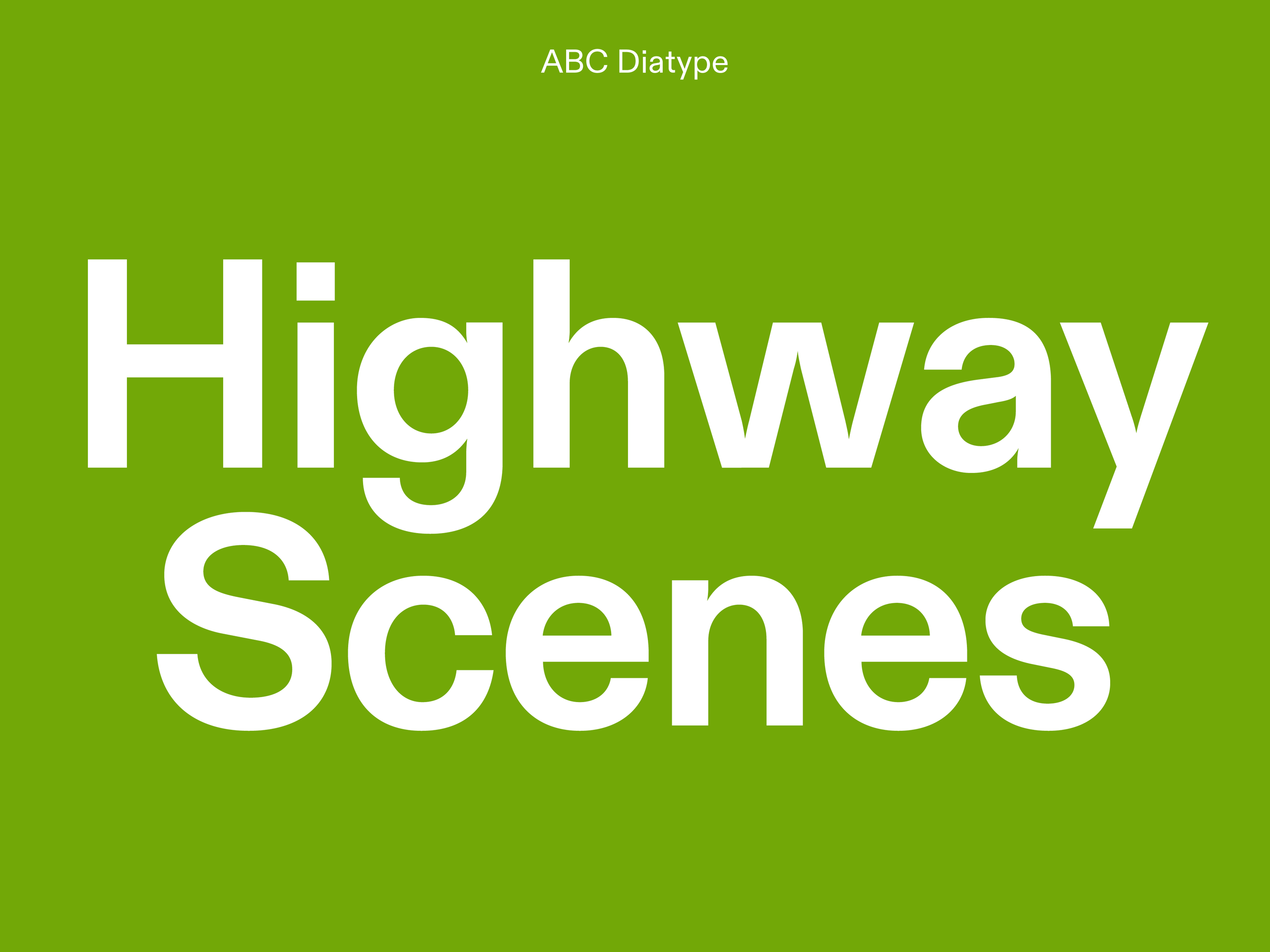
ABC Whyte Hangul, ABC Whyte Inktrap Hangul
우선, 새로운 한글 폰트인 화이트 「ABC Whyte Hangul」 얘기를 빼놓을 수 없겠죠! 많은 산돌구름 사용자들이 출시를 간절히 요청해 왔던 폰트이기도 합니다.
디나모의 베스트셀러 중 하나인 「ABC Whyte」 시리즈는 깔끔한 인상의 산세리프 폰트인데요, 독특한 디자인의 소문자 'a' 와 'g'가 매력을 더해주죠. 디나모의 또 다른 베스트셀러 「ABC Favorit Hangul」 에서도 협업한 윤민구 디자이너가 또 함께 한글 확장 제작에 참여했습니다.
「ABC Whyte」는 ‘잉크트랩(Inktrap)’ 스타일이 있다는 점이 큰 특징인데요. 잉크트랩은 활판 인쇄 시 잉크가 뭉쳐 보이는 것을 방지하기 위해 획과 획이 만나는 부분에 일부러 홈을 파듯 디자인한 디테일이지만, 오늘날에는 그래픽적인 재미를 더하는 요소로 많이 쓰이고 있습니다.
2025 수원시립미술관 10주년 특별전 《모두에게: 초콜릿, 레모네이드 그리고 파티》. Design by 파이카 Paika
라틴보다 구조가 훨씬 복잡한 한글에 잉크트랩 디테일을 자연스럽게 녹여내는 일은 쉽지 않은데요, 「ABC Whyte Inktrap Hangul」은 구조가 단단하고 안정적이면서도 시각적인 재미도 놓치지 않은, 정말 완성도 높고 신선한 인상의 폰트입니다. 많은 분들이 즐겨 써주실 모습이 벌써 기대되는 폰트에요.
ABC Arizona
『디나모 라이프 B』에서 또 눈여겨 볼만한 폰트는 「ABC Arizona」가 있을 것 같은데요. 「ABC Arizona」는 산세리프부터 세리프까지, 전혀 다른 다섯 가지 스타일 Sans, Flare, Mix, Text, Serif 을 하나의 통일된 뼈대로 풀어낸 혁신적인 슈퍼패밀리입니다. 한 지면 안에서 산세리프 폰트와 세리프 폰트가 둘다 필요할때, 이 패밀리를 활용한다면 전체적으로 조화롭게 통일감을 줄 수 있겠죠?
ABC Maxi
디나모 특유의 유쾌함과 실험 정신이 잘 드러나는 폰트를 찾고 계시다면, 「ABC Maxi」를 추천드리고 싶어요. 스파게티처럼 유연한 곡선과 예상치 못한 포인트에서 각지게 마무리한 느낌이 독특한 인상을 주는 폰트입니다. 또한 「ABC Maxi」는 Round, Round Mono, Sharp, Sharp Mono 네 가지 서브패밀리로 구성되어 있어, 스타일과 굵기를 자유롭게 실험하며 재미있게 활용할 수 있을 거예요.
Ways – Driving School. Branding by Studio Bergini
ABC Repro
디나모의 폰트들을 쭉 살펴보면, 패밀리 구성에 하나쯤은 눈에 띄는 독특한 스타일이 포함되어 있다는 공통점이 있는데요. 「ABC Repro」 역시 마찬가지입니다. 글자 주변을 둥글게 감싸 버튼처럼 보이게 해주는 기능이 포함되어 있어, 별도 작업 없이도 그래픽 요소처럼 활용할 수 있습니다.
No You See Me Moria Action Book. Design by Raoul Gottschling
글자의 획 끝을 수직과 수평으로 또렷하게 다듬은 지오메트릭한 구조로, 깔끔하고 현대적인 인상이 필요한 다양한 프로젝트에서 폭넓게 쓰일 수 있을 것 같아요.
ABC Diatype
마지막으로 소개할 「ABC Diatype」은 디나모를 대표하는 또 하나의 산세리프 패밀리로, 많은 분들이 기다려온 폰트일 거예요. 군더더기 없이 깔끔하고 정제된 느낌의 산세리프 폰트랍니다.
ABC Monument Grotesk
어디에나 잘 어울리는 뉴트럴 산세리프를 찾는다면? 바로 이 폰트입니다. 이번 업데이트를 통해, 「ABC Monument Grotesk」 가 10종에서 16종으로 종수가 확장되었습니다.
Data Centers. Design by Jonas Vögeli (Hubertus)
「ABC Monument Grotesk」는 고정폭 버전인 Mono, 그리고 고정폭의 느낌을 살리면서도 가독성을 챙긴 Semi-Mono 버전도 제공해 더욱 다채로운 표현이 가능한데요. 최근 업데이트와 함께 이 두 서브 패밀리도 Regular, Italic 만 제공되던 2종에서 14종으로 대폭 확장되어, 보다 다양한 디자인 환경에 맞춰 사용할 수 있게 되었어요. 『디나모 라이프 A』 기존 사용자 분들도 반길 기쁜 소식입니다.
ABC Favorit, ABC Favorit Hangul
다음으로 주목할 폰트는 디나모를 대표하는 폰트 중 하나인 「ABC Favorit」과, 윤민구 디자이너와의 협업을 통해 한글로 확장된 「ABC Favorit Hangul」입니다.
Leaves – Adriaan De Roover. Designed by Ward Heirwegh
「ABC Favorit」의 라틴은 전반적으로 매우 뉴트럴한 구조를 기반으로 하지만, 소문자 ‘f' 't’ ‘y’ 등에서 드러나는 기하학적인 디테일 덕분에 조판했을 때 은은하게 엣지 있는 인상을 준답니다.
Suh Jihyoung: Shaking Lines. Design by Jin & Park, Jin Dallae and Park Woohyuk
이러한 라틴의 특징은 한글에서도 ‘ㅅ’, ‘ㅈ’과 같은 자소의 대칭적인 형태를 통해 잘 반영되어 있죠. 또한, 각 단어의 첫 글자와 마지막 글자가 밑줄로 연결되어 독특한 효과를 주는 '라이닝' 스타일도 지원하는데요, 특별한 강조가 필요한 상황에서 활용해 보시길 추천드립니다.
ABC Galapagos
디나모는 스위스 스타일의 깔끔하고 범용적인 폰트뿐 아니라, 실험적인 성격의 폰트들도 다양하게 선보이고 있어요. 그중에서도 「ABC Galapagos」 시리즈는 재미있는 구조의 모듈형 폰트로, 다양한 스타일을 조합해서 그래픽적으로 활용하기에 딱 좋습니다. 직선, 곡선, 대각선 같은 다양한 스타일을 자유롭게 섞어 쓸 수 있고, 글자의 위치를 위아래로 조정할 수 있는 기능까지 더해져, 마치 놀이하듯 재미있게 활용할 수 있는 폰트입니다.
Posters for Lustgarten parties in Berlin, renderings by Oliver Laric